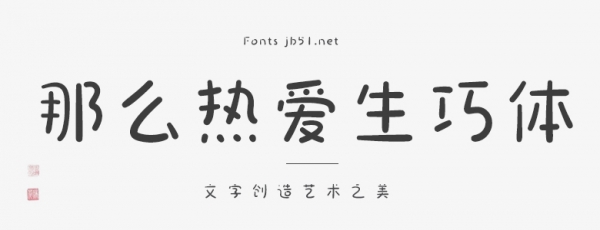
那么熱愛生巧體是一款非??蓯鄣氖謱懰囆g(shù)字體,字型俏皮可愛,具有強(qiáng)烈的視覺沖擊力,適用于包裝設(shè)計(jì)、電商、品牌名稱、漫畫、影視綜藝、游戲、各類商業(yè)海報(bào)、戶外廣告標(biāo)題等設(shè)計(jì)領(lǐng)域,歡迎喜歡此字體的朋友前來下載使用。